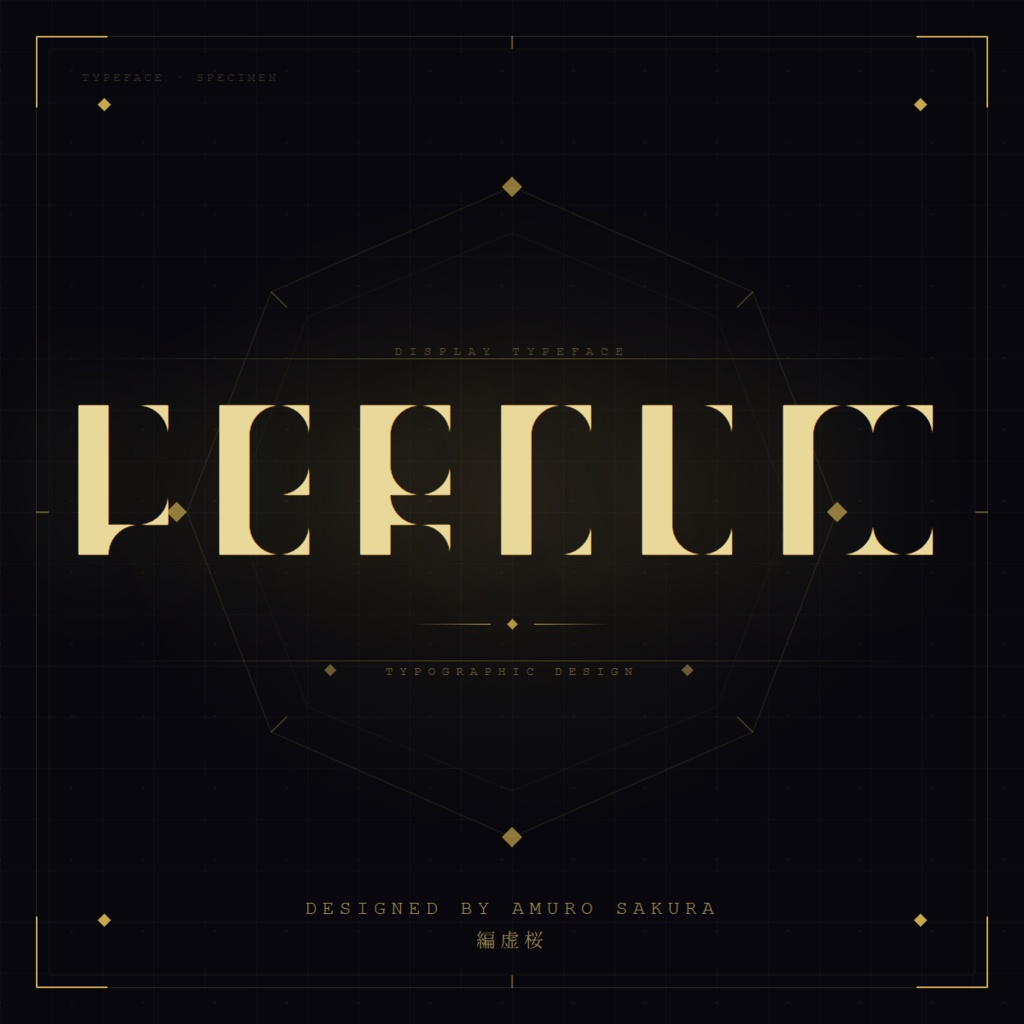
AmuroSakura【商用利用可能!】フォント:VernumーヴィルナムDigital1,000 JPYAdd to CartBuy a GiftAbout Giftこんにちは。編虚桜です。 ファンタジーかつデザイン性の強いフォント。 高級感と荘厳さを重視し、デザイン性を優先したフォントとなっております。概要Vernumーヴィルナムは、商用利用が可能なフォントです。 商品のご購入後、zipファイル同梱の利用規約 [ license.txt ] をご確認の上、ご利用ください。注意事項・利用規約商用利用:可能 クレジット表記:フォントの製作者および本ソフトの名称を表記 再配布:禁止 改変後の配布:禁止 権利帰属: 編虚桜に帰属AmuroSakuraVisit FANBOX!Fonts【商用利用可能!】フォント:Claiz — クライツAmuroSakura1,000 JPY3D Tools & Systems【無料!】CINIS ALBIOS : モノトーンなBlenderテーマAmuroSakura0 JPY3D Tools & Systemspalette_one : Blenderのノード構成をプリセット化して、配置!AmuroSakura2,000 JPYFonts商用利用可能フォント!MAESTOSO : メズトーゾAmuroSakura500 JPYFonts英字フォント【MAQUIA :マキア】AmuroSakura500 JPYFonts異世界風フォント「さぐらんど」AmuroSakura500 JPY3D Tools & SystemsRenderOne ―レンダリングをワンクリックで高速化するアドオン—AmuroSakura1,000 JPYSee More